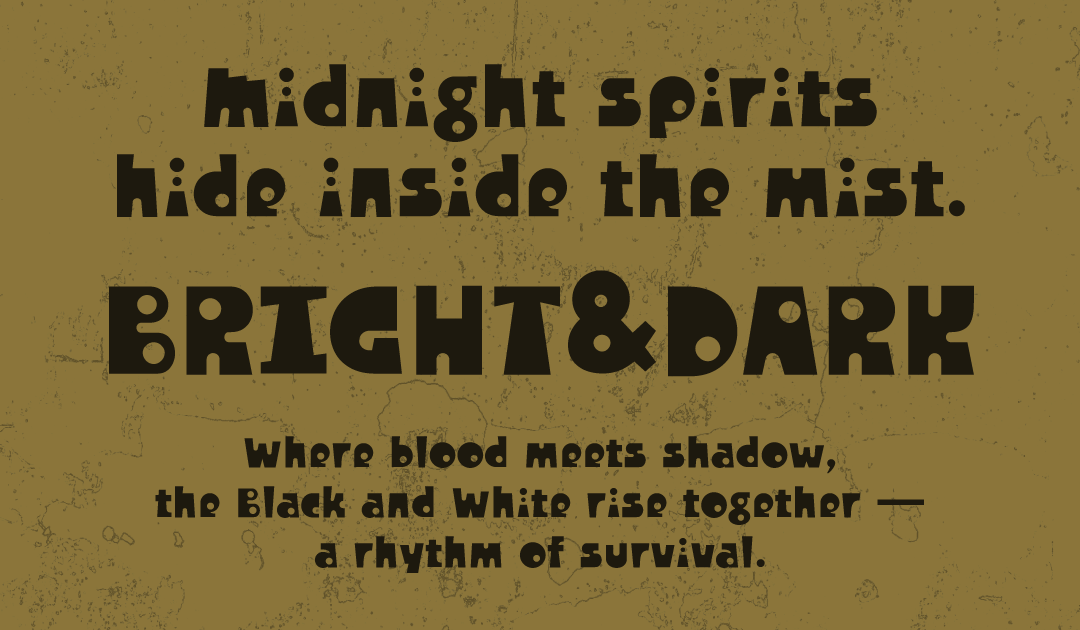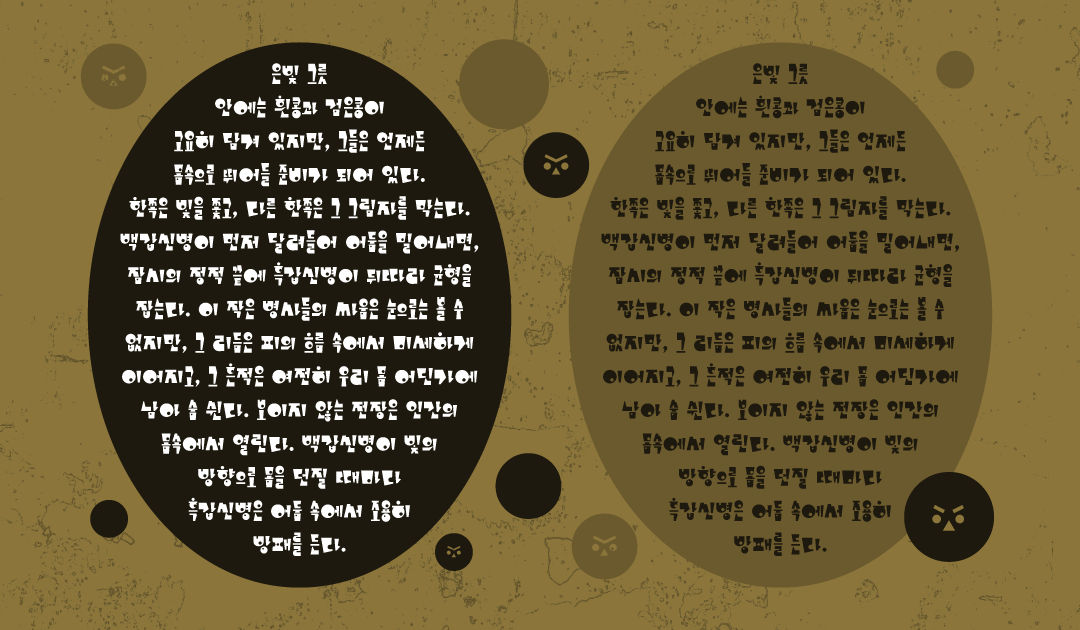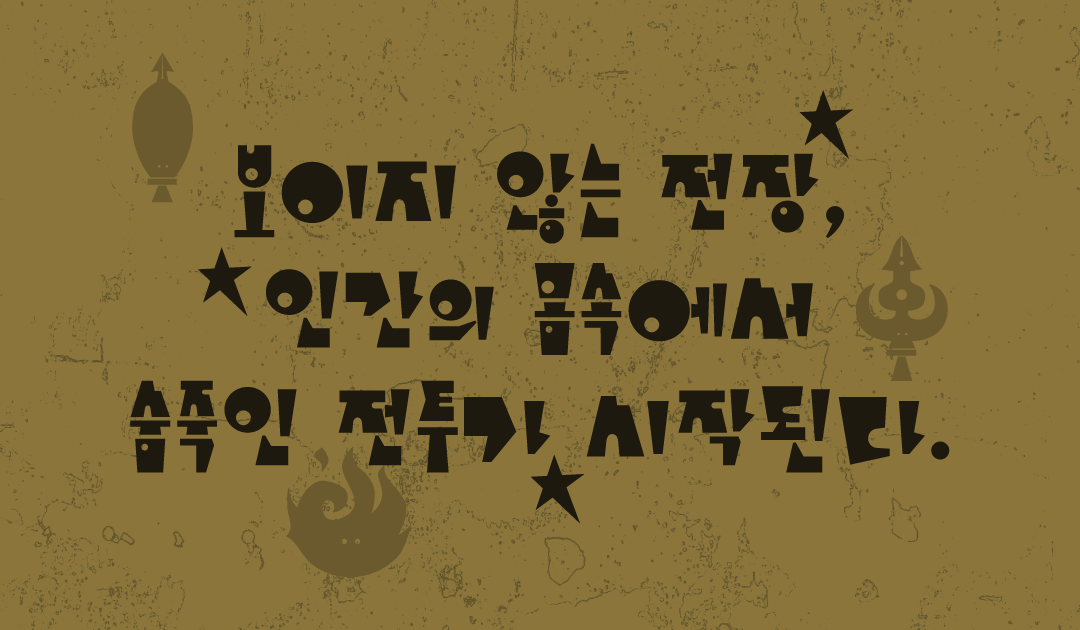
다양한 컨셉으로 활용이 가능하고 독특한 디자인 요소가 많은 서체 시리즈. 개성있는 디테일로 시각적 재미를 더하고 풍부한 이야기를 담을 수 있는 서체이다.
폰트 설명
요괴 프로젝트는 “한국 요괴”라는 독창적인 주제를 바탕으로 한 신규 폰트 패밀리입니다. 한국적인 요소와 요괴라는 존재의 흥미로움을 결합하여, 기존에 없던 독자적인 서체 세계를 구축하고자 했습니다. 『한국 괴물 백과』에서 소개된 요괴 중, 글자 형태로 구현하기에 적합하면서도 대중에게 잘 알려지지 않은 요괴들을 선별했습니다.
흑갑백갑, 비유설백, 계룡은 각각 독특한 이야기를 지니고 있으며, 그 신비롭고 기괴한 존재감 속에 한국적 요소와 친근한 귀여움을 시각적으로 결합하여 독창적인 폰트로 재해석했습니다.
<한글 디자인>
흑갑백갑은 독특하고 귀여운 매력을 지닌 캐릭터들의 비규칙적인 조화로움이 있는 폰트입니다. 글자와 도형의 경계에 있는 수준으로 단순화하여, 원·네모·삼각형의 기하학적 형태를 살렸습니다. 크기가 큰 초성으로 인해 글자가 천제적으로 귀여운 인상을 줍니다.
탈네모꼴 형태이며 모임꼴과 받침 유무에 따른 너비와 크기 차이를 다양하게 주었습니다. 복합모음꼴은 작게, 세로모임꼴은 길고 좁게, 가로모임꼴은 초성을 크게 하여 가로로 넓어지게 설정했습니다. 또한 ‘ㄹ’ 받침이 포함될 때는 글자의 크기가 더욱 커지도록 하여 풍성한 시각적인 재미와 이렇게 각기 다른 크기의 글자들이 모였을 때 신선한 조형성과 역동성을 만들어내며, 자유로운 글줄로 유쾌하게 표현됩니다. 콩의 동그란 외형에서 착안해 'ㅇ'을 먼저 디자인하고, 그 도형적 특징을 다른 자소에 적용했습니다. 'ㅇ'의 속공간은 동그랗게 파여 백갑신병이 몸 안으로 들어가 싸우는 장면을 형상화했고, 백갑신병이 힘겨워할 때 흑갑신병이 투입된다는 설정에 따라 'ㅎ'의 상투를 동그랗게 디자인해 흑갑신병이 위에서 대기하는 모습을 표현했습니다. 자소 중 ㅁ,ㅇ,ㅂ, ㅎ 과 같은 글자에서는, 그 속의 내부 공간을 ‘콩’이 실제로 움직이는 듯한 모습 그리고 이 콩의 방향과 크기를 조절하여 전투 상황을 만들어 표현하기 위해 베리어블 기능을 이용했습니다. 정지된 글자에 움직임을 부여함으로써 생동감을 더하여 단순한 기능적 확장을 넘어, 서사를 극대화하는 장치로 작동합니다.
<라틴 디자인>
라틴과 한글 글자 간 통일감을 위해 내측 곡선에 동일한 원형 곡률을 적용하였고, ‘i’의 점(dot)을 하나 더 추가해 흑갑신병과 백갑신병의 존재감을 상징화했습니다. 전체적으로 직선 대신 사선을 사용해 폰트가 딱딱함 보다는 유쾌함과 함께 리듬감을 더합니다.
<딩벳>
딩벳은 각 폰트당 10개로 구성되어 있습니다. 동양의 상징인 음양 기호 1개, 음양오행의 다섯 원소 5개, 그리고 각 요괴의 특성을 담은 딩벳 4개입니다. 공통적으로 들어가는 기호는 6가지이며, 같은 공통 기호더라도 요괴의 분위기나 특징에 따라 다르게 제작되었기 때문에 3가지 폰트의 공통기호 딩벳을 비교하면서 보는 재미가 있습니다.
공통 음양기호: 음양기호에 동그란 원이 2개가 있어 베리어블로 크기를 함께 조절 가능
음양오행 : 물, 불, 나무, 산, 검(쇠) 전체적으로 귀엽고 단순한 이미지의 콩에 맞춰 캐릭터화
캐릭터 딩벳 : 흑갑신병과 백갑신병이 전투 시 쓰는 무기로 구성.
-요괴: 흑갑신병과 백갑신병
-무기1: 월도
-무기2: 화살촉 (우리나라 전통 화살 7종 중 2종을 선택)
-무기3: 도끼